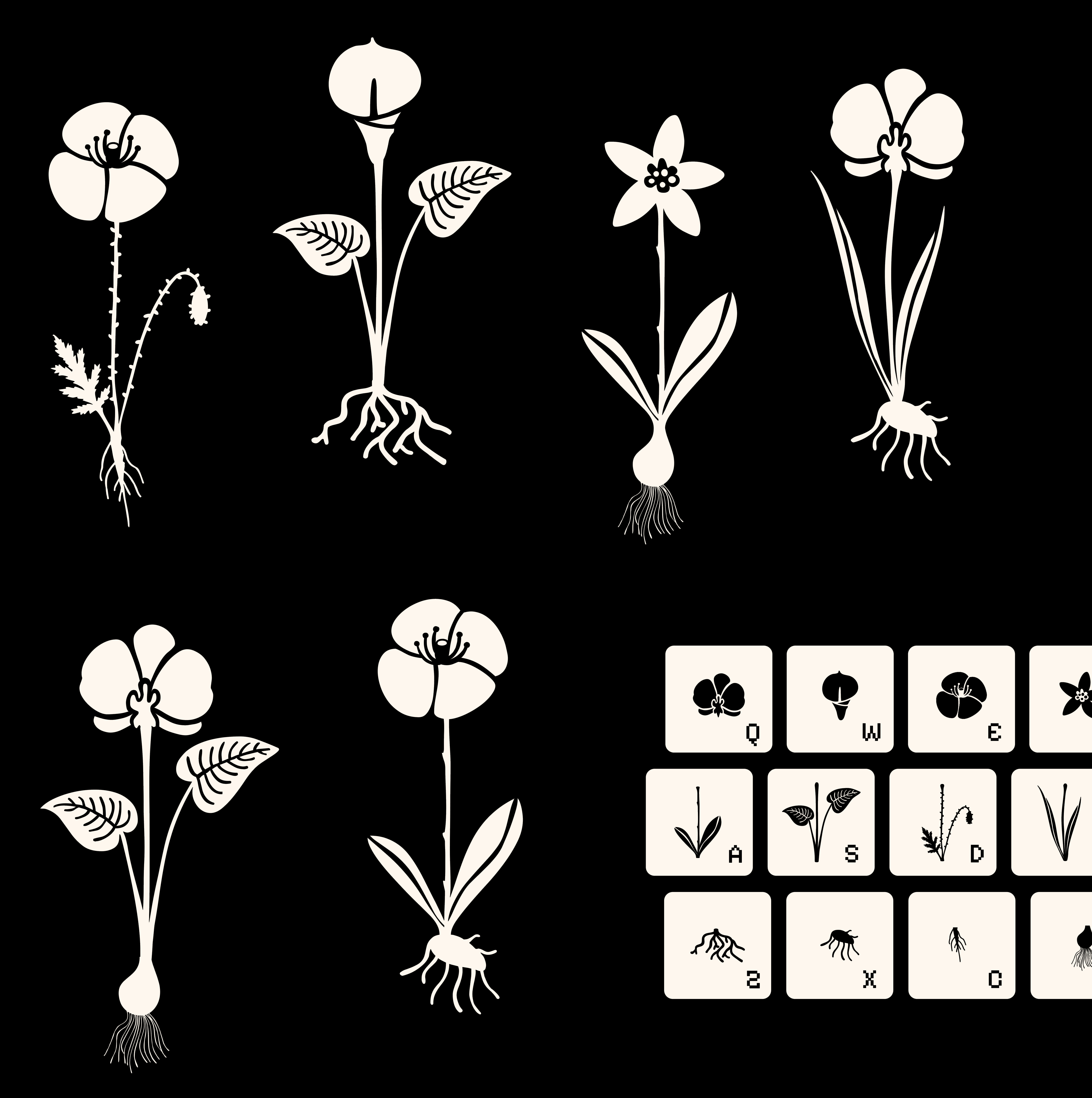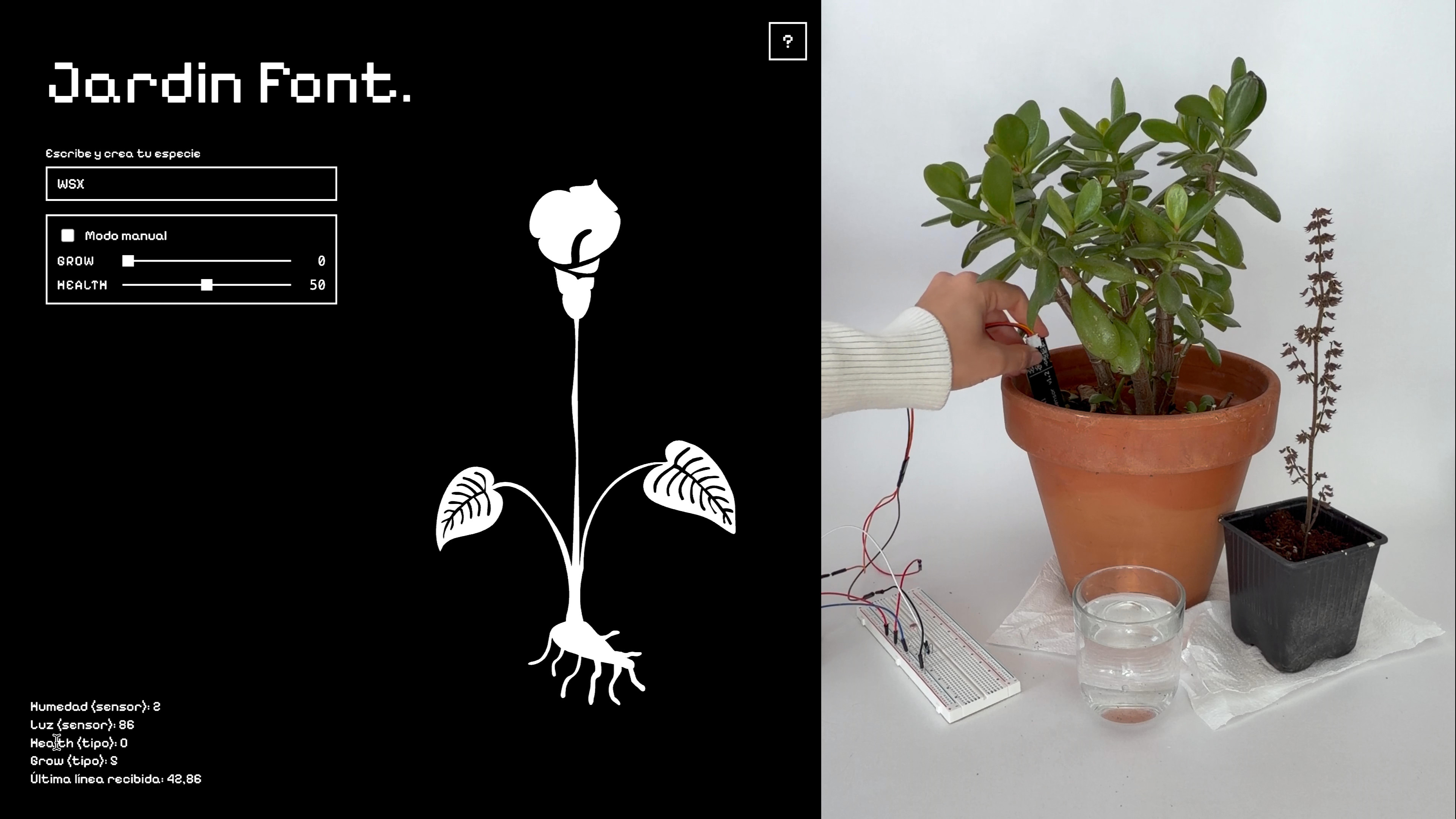
Este proyecto desarrolla un sistema tipográfico concebido como un organismo vivo que reacciona en tiempo real a las condiciones ambientales. La propuesta captura datos físicos del entorno para representar el estado de vitalidad de las plantas mediante la transformación morfológica de los glifos. El sistema se estructura como una tipografía modular que permite al usuario construir glifos personalizados mediante la combinación de tres elementos fundamentales: flor, tallo y raíz. La variación morfológica se encuentra articulada a través de dos ejes de variación, health y grow. Mediante sensores de humedad y luz conectados vía Arduino, el tipo adopta un comportamiento interpretativo en el que el crecimiento se detiene o la forma se degrada ante condiciones adversas. Esta lógica visualiza la fragilidad de los sistemas vivos al convertir el estado biológico de la planta en una dinámica de expansión o deterioro gráfico.
Al igual que The Climate Crisis Font, el proyecto visualiza la fragilidad del ecosistema al condicionar la morfología del glifo según el contexto ecológico, provocando una erosión formal cuando las condiciones del entorno resultan adversas. Para resolver su ejecución como sistema modular, el proyecto recupera la técnica de The Guilty Hand Font al fragmentar el cajetín tipográfico en tres segmentos verticales. Esta estructura permite que, mediante la aplicación de reglas de tracking negativo, glifos independientes que se suceden en la línea de escritura se solapen entre sí, convirtiendo la progresión horizontal en un proceso de ensamblaje visual que conforma una unidad gráfica única y compleja. En el plano de la morfogénesis tipográfica, la propuesta converge con Mandacaru Color Font, Hypha y BioTipo al integrar lógicas de crecimiento orgánico donde la forma, lejos de ser estática, brota y se expande simulando fases biológicas reales. Desde una perspectiva de comportamiento sistémico, el proyecto se aproxima a Physarum Type Tool, trascendiendo la ilustración botánica para operar como un organismo digital simulado que reacciona y lucha por su supervivencia en función de los recursos disponibles. En su dimensión técnica, la captura de luminosidad y humedad mediante hardware físico expande las bases de medición ambiental exploradas en el prototipo número tres.
La arquitectura de Jardín Font articula el modelo mediante una relación basada en la captación de variables físicas, donde los valores de humedad y luminosidad actúan como datos de entrada. El sistema emplea una función normalizadora ejecutada en p5.js que procesa las lecturas de los sensores para adaptarlas a los rangos operativos del espacio de diseño de la tipografía, aplicando una lógica condicional jerárquica en la que el crecimiento solo se activa si los niveles de salud son óptimos, de modo que una carencia en la luz bloquea el desarrollo independientemente de la humedad disponible. A partir de estos datos, la función significativa ejecuta una lógica de simulación biológica vinculando el bienestar de la planta con la expansión y vitalidad del trazo. Este sistema genera valores transformados que alteran la estructura del glifo, validando la capacidad del modelo para ampliar los procesos de significación al convertir la tipografía en una interfaz sensible que comunica el estado vital de la planta representada.
- Función: Visualización de datos
- Contexto: Investigación / Experimental
- Institución: Escuela Superior de Diseño de Madrid
- Grado de interactividad: Interacción débil o reactiva
- Input multimodal: Sí
- Tipo de input: Datos externos y cursor
- Tipo de output: Transformación morfológica
- Tecnología empleada: Tipografía variable, Arduino, p5.js
- Alfanumérica: No
- Mantiene codificación textual: Sí